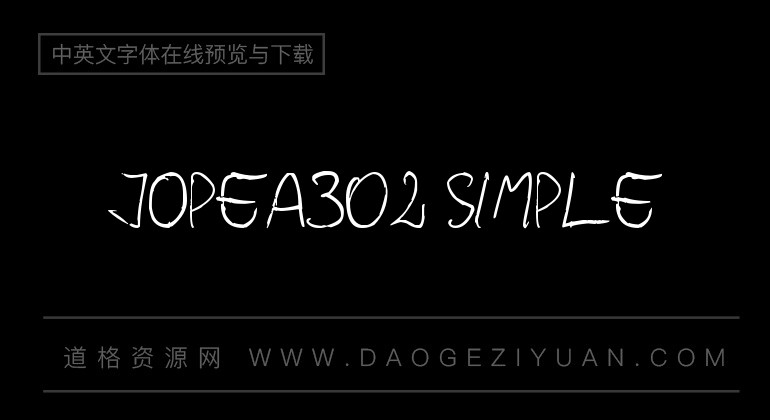
Jopea302 Simple
Jopea302 Simple 是一款简洁优雅的英文字体,它采用精致的线条,为每个字母添加了精心的细节,使它们看起来更加清晰,更加有趣。它的字体特点是简洁、精致、细腻,能够很好地表现出文本的细节,让文本看起来更加精致清晰。这款字体适用于设计师、印刷商和出版商,可以用于制作各种类型的文档、图书、海报、报纸等。
Jopea302 Simple是一款非常不错的手写艺术字体,具有很好的视觉感,适合于文化类的宣传设计、商业类品牌的广告和产品包装设计以及个性化文字排版等较多场景。